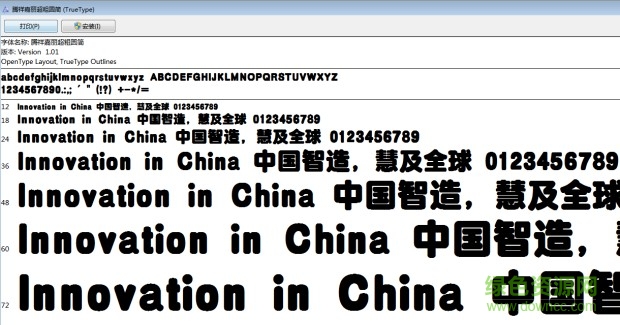
騰祥嘉麗超粗圓簡字體是一款非常時(shí)尚也非?;馃岬淖煮w,這款字體字形超粗,適合作為重點(diǎn)字體的格式,非常引人注意哦,有需要的就來綠色資源網(wǎng)下載吧!
騰祥嘉麗超粗圓是應(yīng)用于設(shè)計(jì)方面的一款中文字體。該字體線條粗壯有力,字形端正大方得體,整體效果非常的出色,并且字庫完整,可用于藝術(shù)設(shè)計(jì)、包裝印刷、簽名設(shè)計(jì)、圖形設(shè)計(jì)等領(lǐng)域。